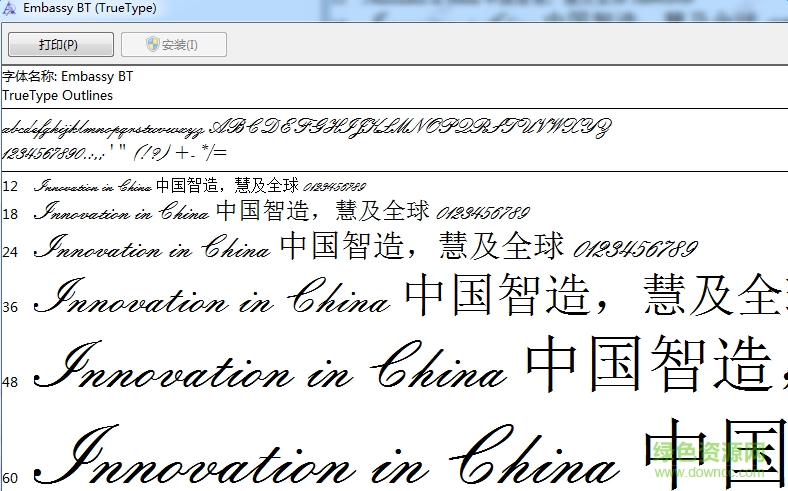
embassy字體
embassy bt字體是一款應(yīng)用于廣告設(shè)計方面的個性字體,該字體可廣泛應(yīng)用于平面設(shè)計、廣告設(shè)計、報紙雜志、正文標(biāo)題等領(lǐng)域,喜歡的網(wǎng)友可免費下載收藏。
embassy bt字體是一款極具個性的英文字體,字體非常飄逸,有一種優(yōu)雅美。喜歡的朋友可以來綠色資源網(wǎng)下載體驗!